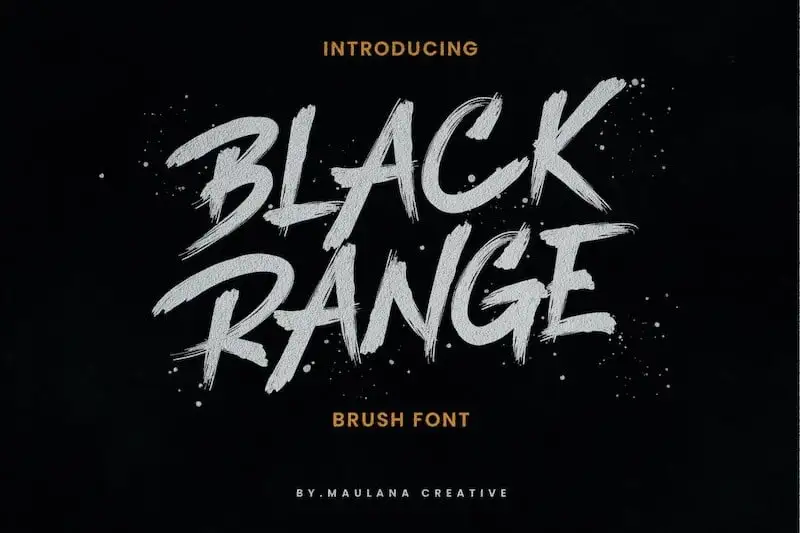
Black Range Brush Font – Download Grátis
A Black Range Brush Font é uma fonte Display ideal para projetos visuais criativos. Desenvolvida pela Maulana Creative, essa tipografia tem um estilo à mão livre que consegue capturar a essência de qualquer projeto. Perfeita para branding, logomarcas, designs de camisetas, postagens nas mídias sociais, anúncios e embalagens de produtos, além de design de produto, rótulos, impressões digitais, convites e material de estação criativa. É uma ferramenta perfeita para artesãos digitais e designers que procuram transmitir personalidade em seus projetos visuais. Engane-se se acha tão versátil quanto a própria descrição. A Black Range Brush Font está aqui para deixar seu trabalho de design ainda mais especial.